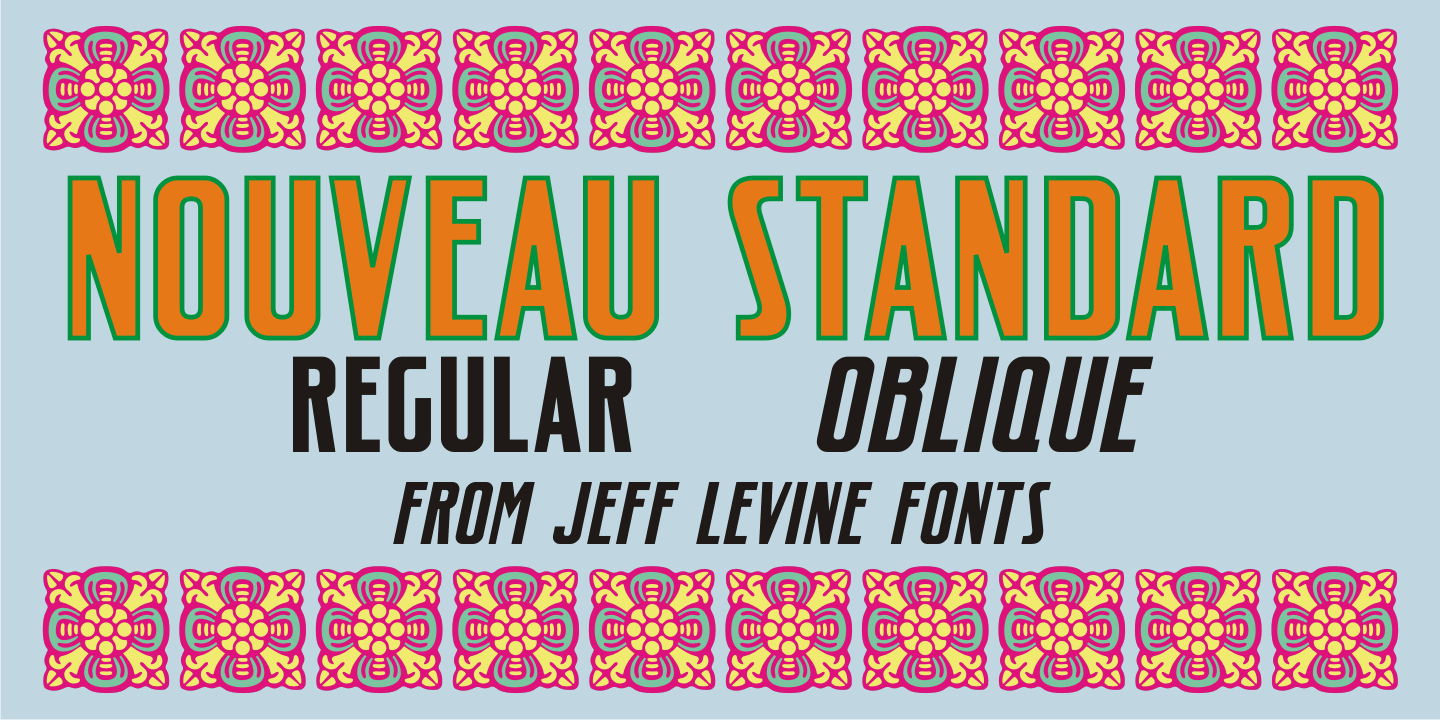
На обложке нотного издания 1912 года "Somebody Else is Getting It" использован шрифт, выполненный от руки в стиле модерн с закругленными углами и весьма непристойным названием [хотя в те времена оно, скорее всего, имело более невинный смысл, чем может показаться случайному наблюдателю сегодня].
Теперь он доступен как Nouveau Standard JNL, причем как в обычной, так и в наклонной версии.